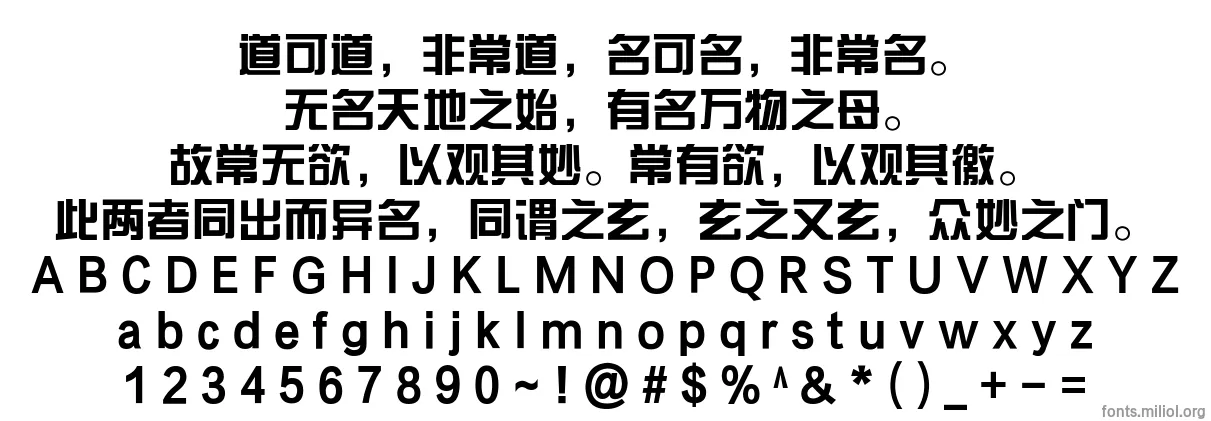
方正综艺_GBK (FZZongYi-M05) (FZZYK--GBK1-0) 字体下载
《方正综艺_GBK:经典字体设计与应用价值》
方正综艺_GBK(FZZongYi-M05)是一款兼具现代感与实用性的中文字体,隶属于方正字库的GBK编码系列。其设计以综艺体为基础,笔画粗壮有力,转折处带有圆润处理,整体风格既庄重大气,又不失灵动,适用于标题、广告、品牌标识等需要视觉冲击力的场景。GBK编码支持包括繁体字在内的两万多个汉字字符,兼容性广泛,可满足多场景文本需求。
作为一款商业字体,方正综艺_GBK在印刷品、影视包装和数字媒体中均有出色表现,尤其适合文化宣传、活动海报等主题。使用时需注意版权授权,确保合法合规。其独特的艺术性与功能性结合,使其成为设计师的常用工具之一。